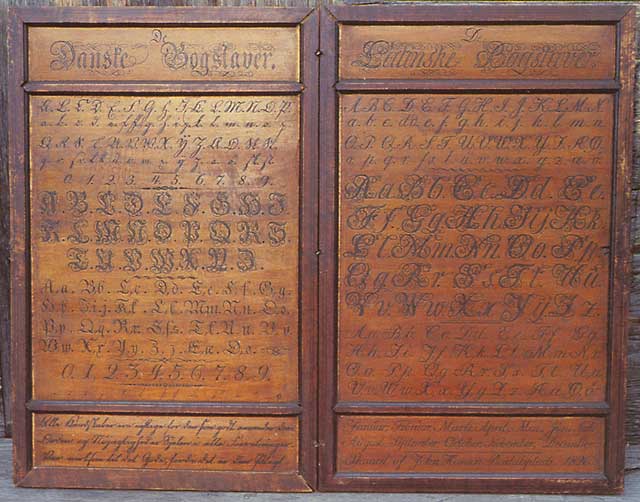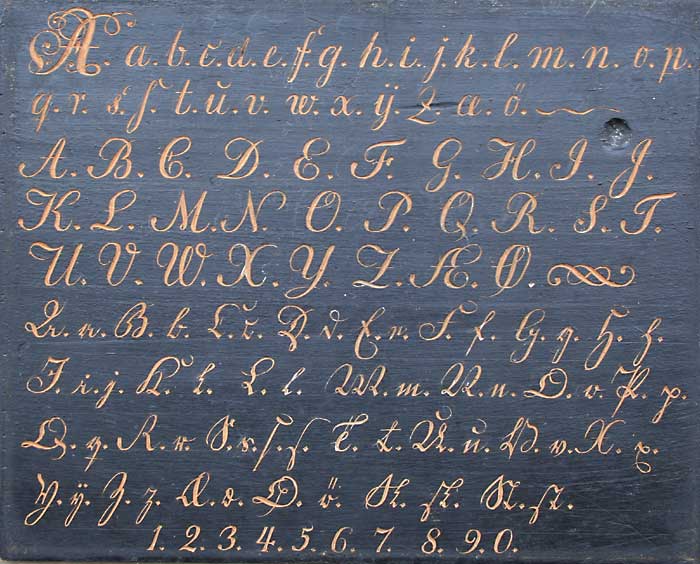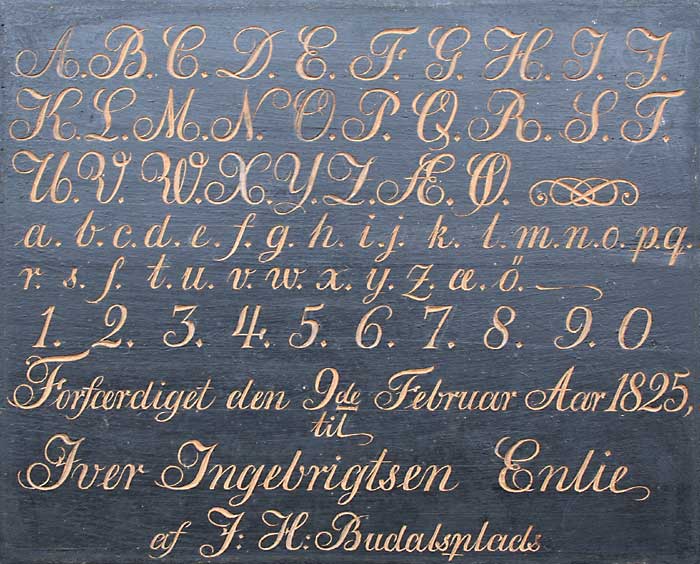
John Hansen Budalsplads (17981874) var en talentfull treskjærer av øskjer, tiner og dåser med utskåret dekor. Men i grafisk sammenheng er det hans produksjon av alfabettavler som er av interesse. Disse viser et stort talent for bokstavskjæring. Det er oppsiktsvekkende at han også skar slike tavler for trykking på papir. Dette gir John Hansen Budalsplads en spesiell plass også i den norske boktrykkhistorien. |
Av Torbjørn Eng Treskjæreren John Hansen Budalsplads er analysert og anerkjent av kunsthistorikerne,(1) men hans skriftskjæring er ikke blitt grundig vurdert så langt.(2) Skriftskjæringen er bemerkelsesverdig både med bakgrunn i dens høye kvalitet, og fordi noen tavler ble skåret med bokstavene som stempler (i relieff) og trykt på papir. Dette er i prinsippet en form for «boktrykk». Vi kjenner til tre ulike alfabet-forskrifter trykt på papir fra John Hansen Budalsplads’ hånd, datert henholdsvis 1827 og 1831. Disse er trykt fra treplater, der skriftbildet står ut av treet (som stempler). Trykkformene er ikke bevart, men vi kjenner seks trykk på papir fra dem. |
Han skar også flere forskriftstavler, der et eller flere alfabeter er skåret inn i treet. Seks slike tavler er kjent. For øvrig er det skjært årstall og noe tekst i mye av hans øvrige produksjon. Alle disse skriftarbeidene daterer seg fra perioden 18201831. Boklig orientering Hans skriftinteresse må ha sprunget ut av hans tilknytning til det skrevne ord. Han var både lese- og skrivekyndig, noe slett ikke alle var på denne tida. Som haugianer var han strengt religiøs, og sikkert en ivrig bibelleser. De fire notatbøkene han har etterlatt seg, der han i detalj beskriver arbeidsmetoder i de håndverkene han praktiserte, viser at han behersket det skrevne ord godt. Skrifttavlene og skrifttrykkene har nok stort sett vært laget for private hjem. En av tavlene har innskåret denne teksten: «Forfærdiget den 9de Februar Aar 1825, til Iver Ingebrigtsen Enlie af J: H: Budalsplads.» I private hjem kan de ha vært både til pryd og til nytte for barn og voksne som skulle lære og praktisere lese- og skrivekunsten. Likedan med de trykte alfabetene, som alle (i hvert fall i dag) er innrammet for å henge på veggen. Som Østby skriver,(2) vil de ha vært nyttige i en tid med sparsom undervisning. Det var omgangsskole kun noen få dager hvert år, og svært få bøker på gardene. Men det kan også være at tavlene og trykkene ble brukt i selve skoleundervisningen. |
Illustrasjon 2: Den mest innholdsrike forskriftstavla Budalsplads skar (1826). Foto fra boka i note (1). |
På en av tavlene han skar, har de gotiske alfabetene overskriften «De Danske Bogstaver» (illustrasjon 2). Gotisk skrift dominerte i Norge på denne tida.(4) Flere år etter at Norge ble løsrevet fra Danmark var denne skriftformen fortsatt «dansk» for John Hansen Budalsplads.(5) Gotisk håndskrift ble undervist i skolen i Norge fram til ca. 1860, da den ble avløst av latinsk skrift. Mange av hans forskriftstavler inneholder både den latinske skriftens håndskrevne og trykte form. Håndskrevet gotisk skrift krever spesialkunnskaper for å leses i dag. De «trykte» gotiske bokstavene Budalsplads skar, var ikke direkte kopier av dem som ble brukt i datidas boktrykk (nemlig den gotiske skriftformen «fraktur»). Hans bokstaver var adskillig mer kalligrafiske og kunstferdig utformet enn disse. Mange av dem har lange utløpere og mange er utstyrt med fine seriffer (se illustrasjon 2), i stedet for de typiske brede bredpenn-avslutningene i gotisk skrift. |
Han skar i et tilfelle også et alfabet med rikt dekorerte gotiske majuskler. Slike ble brukt i titler eller som initial (stor begynnelsesbokstav). Til sammen skar han altså fem alfabeter med gotisk skrift: |
Illustrasjon 3: Den vanskelig lesbare gotiske håndskrift: Her bokstavene R, S og T i majuskel- og minuskel-form, fra en forskriftstavle skåret av John Hansen Budalsplads i 1825. |
Latinsk skrift Kobberstikkernes skrift hadde stor innflytelse, og ble modell for vanlige håndskrifter som utkrystalliserte seg særlig i Storbritannia, bl.a. under navnet «copperplate hand». Da behovet for skriving økte med framveksten av internasjonal handel, spredte den engelske skriveskriften seg internasjonalt og fikk en sterk stilling. Men i de tyskspråklige og nordiske landene fortsatte den gotiske håndskriften å dominere. |
Illustrasjon 4: «Engelsk skriveskrift», som var den latinske skriften Budalsplads skar. Samme tavle som over. |
John Hansen Budalsplads var nok ikke så fortrolig med de latinske trykktypene,(6) som foreløpig i beskjeden grad ble brukt i Norge. De ble anvendt i vitenskapelig litteratur, men stort sett ikke i aviser og religiøs litteratur, som nok var det han først og fremst hadde tilgang til. Unntaket er at latinske eller utenlandske ord som inngikk i en tekst med gotiske typer ofte ble satt med latinske typer. På den mest omfangsrike forskriftstavlen hans (illustrasjon 2), er det til sammen seks latinske alfabeter, men de to alfabetene som står vis-a-vis de gotiske trykktypene (og dermed logisk burde vist latinske trykte bokstaver) adskiller seg nesten ikke fra de to håndskrevne latinske alfabetene. Han skar altså ikke de alminnelige latinske trykte bokstavene (antikva). Til sammen skar han i praksis fire alfabeter med latinsk skrift: |
(6) På et lite drikkekar (illustrasjon 5, under) han laget i 1819, har han riktignok skåret teksten «AAR 1819 J:H:BUDAHLSPLADS» med litt klossete latinske «trykte» bokstaver (antikva majuskler). Men kanskje den lave kvaliteten på disse bokstavene skyldtes at han hadde begrenset erfaring med dem? Fotografert av forfatteren.
Tre skrifttrykk |
Illustrasjon 6: sammenligning av minuskel k i trykkene fra 1827 og 1831. |
Det er likevel så mange likhetstrekk i disse to trykkene at det er nærliggende å tro at grunnlaget er den samme trykkformen. De nye bokstavene kan ha blitt skåret separat og blitt felt inn (montert inn) i trykkformen fra 1827, sammen med et nytt årstall. Dette kan skyldes at enkelte bokstaver var blitt skadet, eller det er et uttrykk for hans skiftende smak. Både forskriftstavlene og de trykte alfabetene inneholder et sett tall. Tallene er skråstilt, og passer til både de gotiske og de latinske håndskriftene, som begge heller til høyre. Men til de «trykte» gotiske alfabetene, som har «rette» bokstaver, harmonerer de ikke så bra. Den mest omfangsrike skrifttavlen (illustrasjon 2) inneholder også endel skilletegn og innskuddstegn, som punktum og sitattegn. |